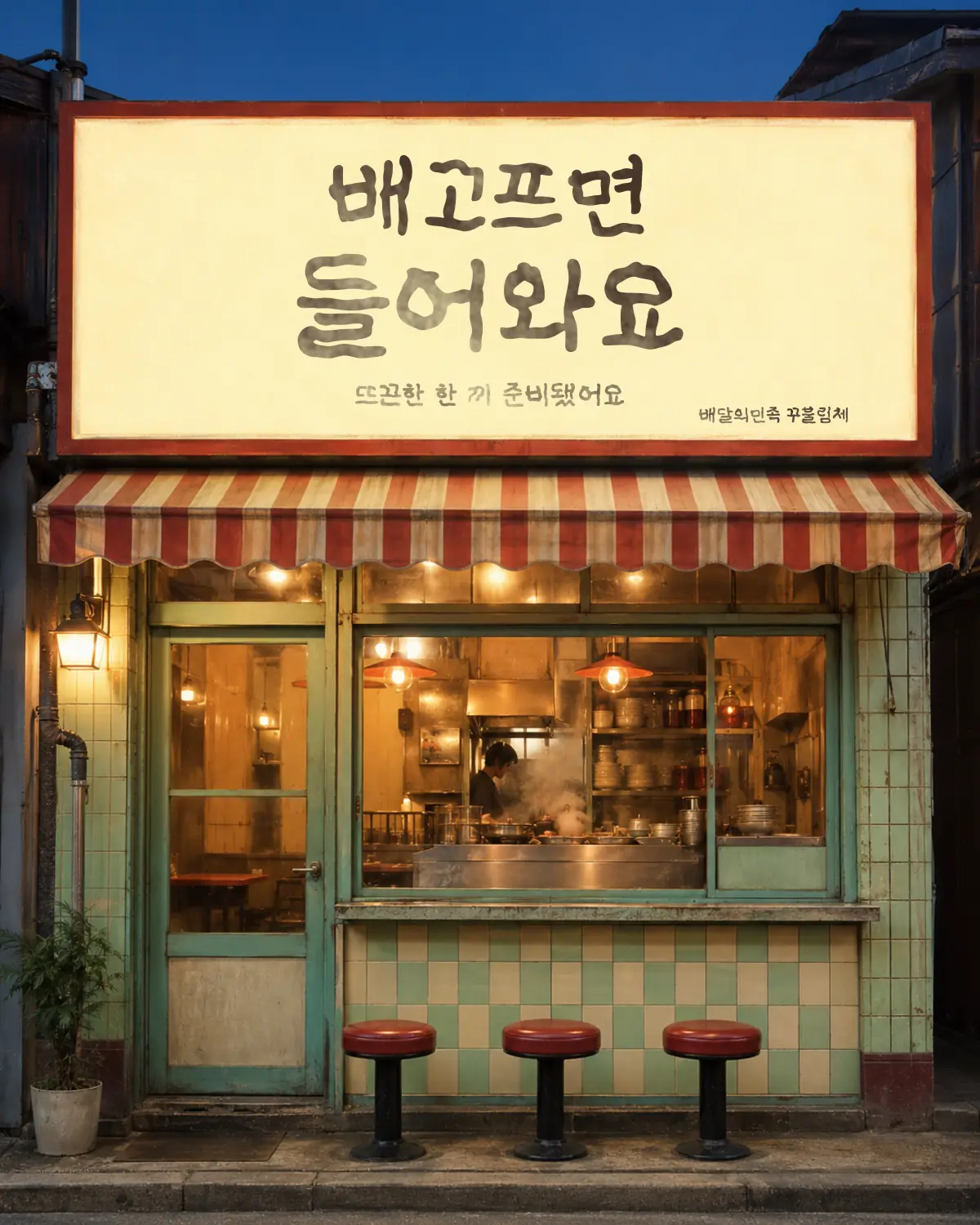
배달의민족 꾸불림체 — 우아한형제들에서 배포하는 무료 폰트입니다. 굴림체를 반듯하게 다듬는 대신 자유롭게 구부려 자연스러운 멋을 살린 손글씨체
우아한형제들이 2024년 한글날에 맞춰 내놓은 열두 번째 배달의민족 서체입니다. 앞선 서체들이 옛 간판을 되살린 것과 달리, 이 서체의 출발점은 실제 간판이 아니라 **다른 폰트에 대한 대구**입니다.
이름이 그 관계를 그대로 보여 줍니다. 꾸불리다는 구부리다의 센말인 꾸부리다의 강원 지역 방언인데, 굴림체가 굴리다에서 이름을 얻은 방식을 그대로 따온 것입니다. 제작사 설명도 그렇게 이어집니다. 한양정보통신의 굴림체가 고딕체를 둥글게 굴려 가독성을 확보했다면, 이 서체는 굴리지 않고 꾸불려 자연스러운 것이 특징이며, 두서가 없거나 경직되어 보이는 글에 자유분방한 파마끼를 더해 준다는 것입니다.
파일에서 재어 보면 받침이 붙을 때 글자 높이가 달라지는 탈네모틀이고 낱자가 가로로 퍼져 있어, 글줄이 일부러 흔들립니다. 굵기는 하나이고 현대 한글 11,172자를 모두 담았습니다.